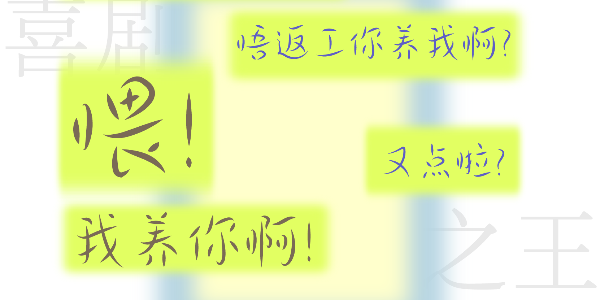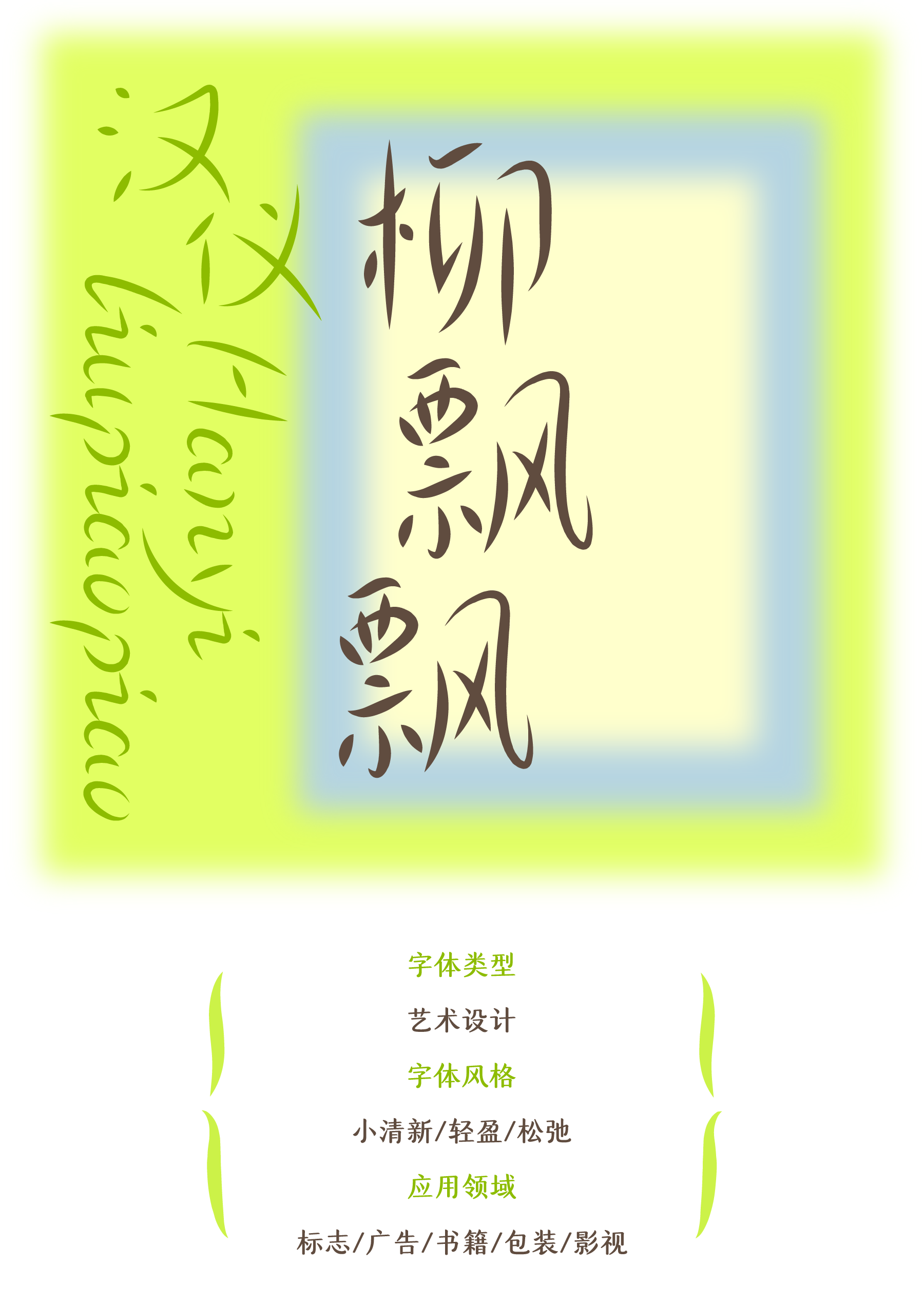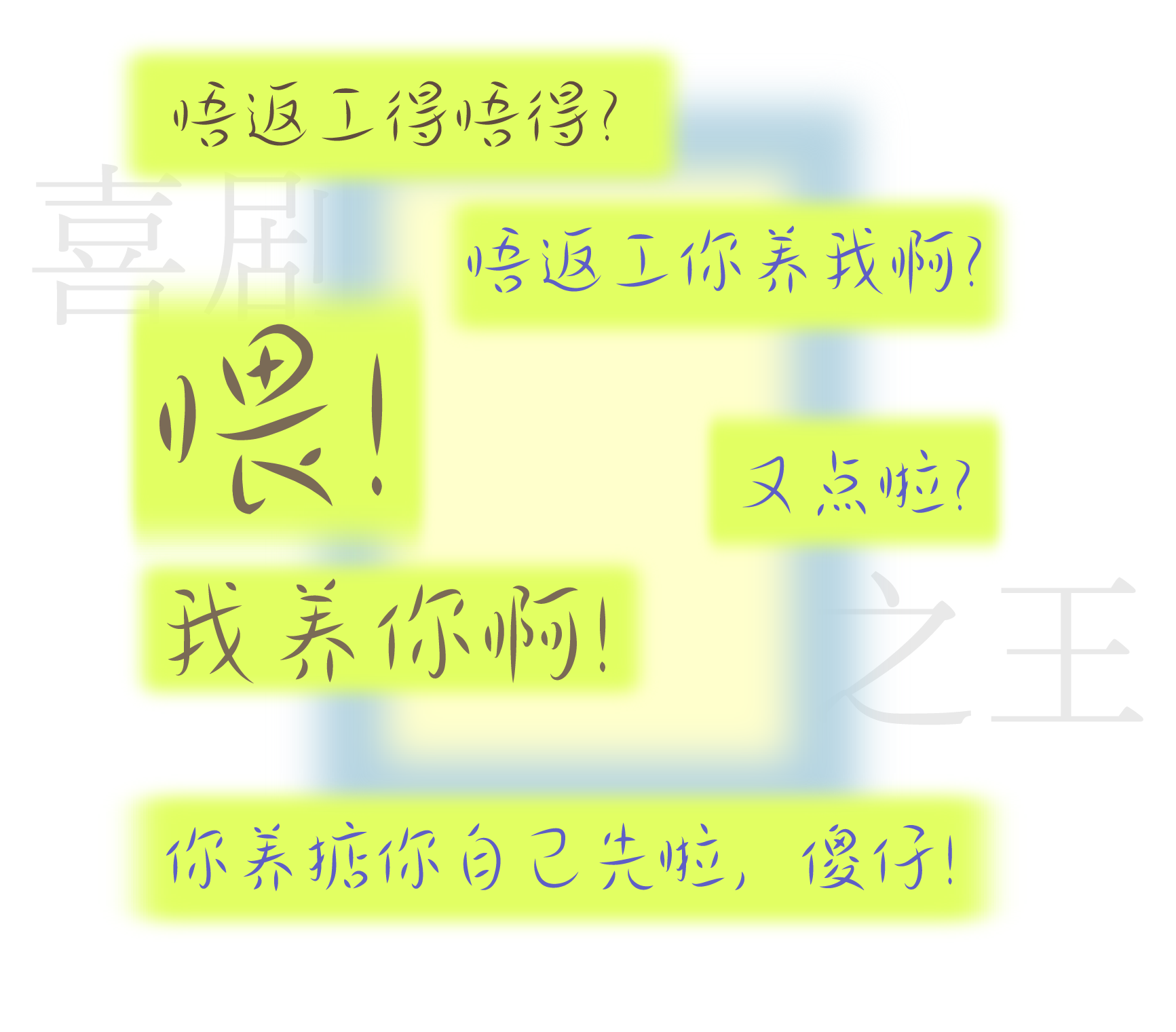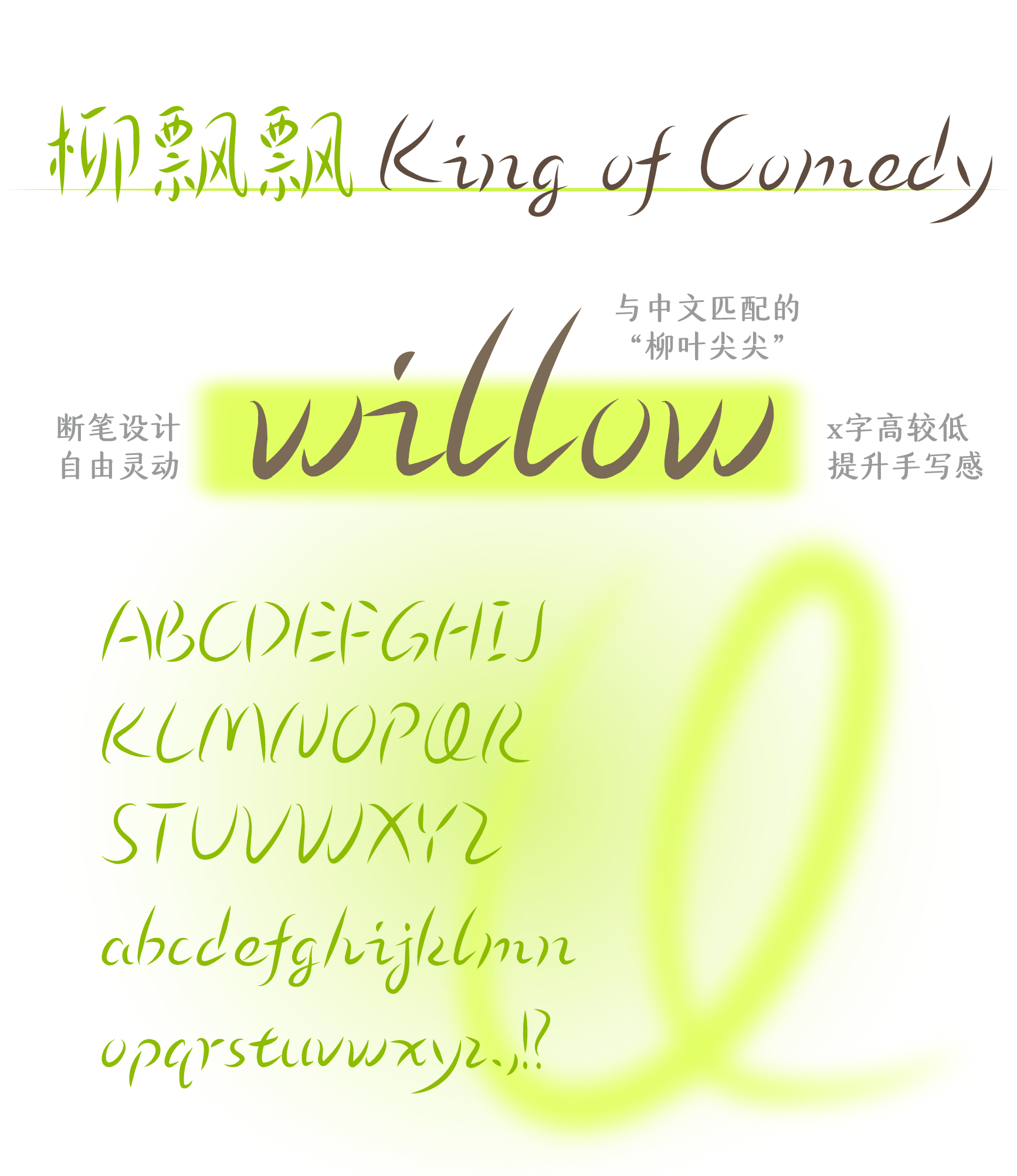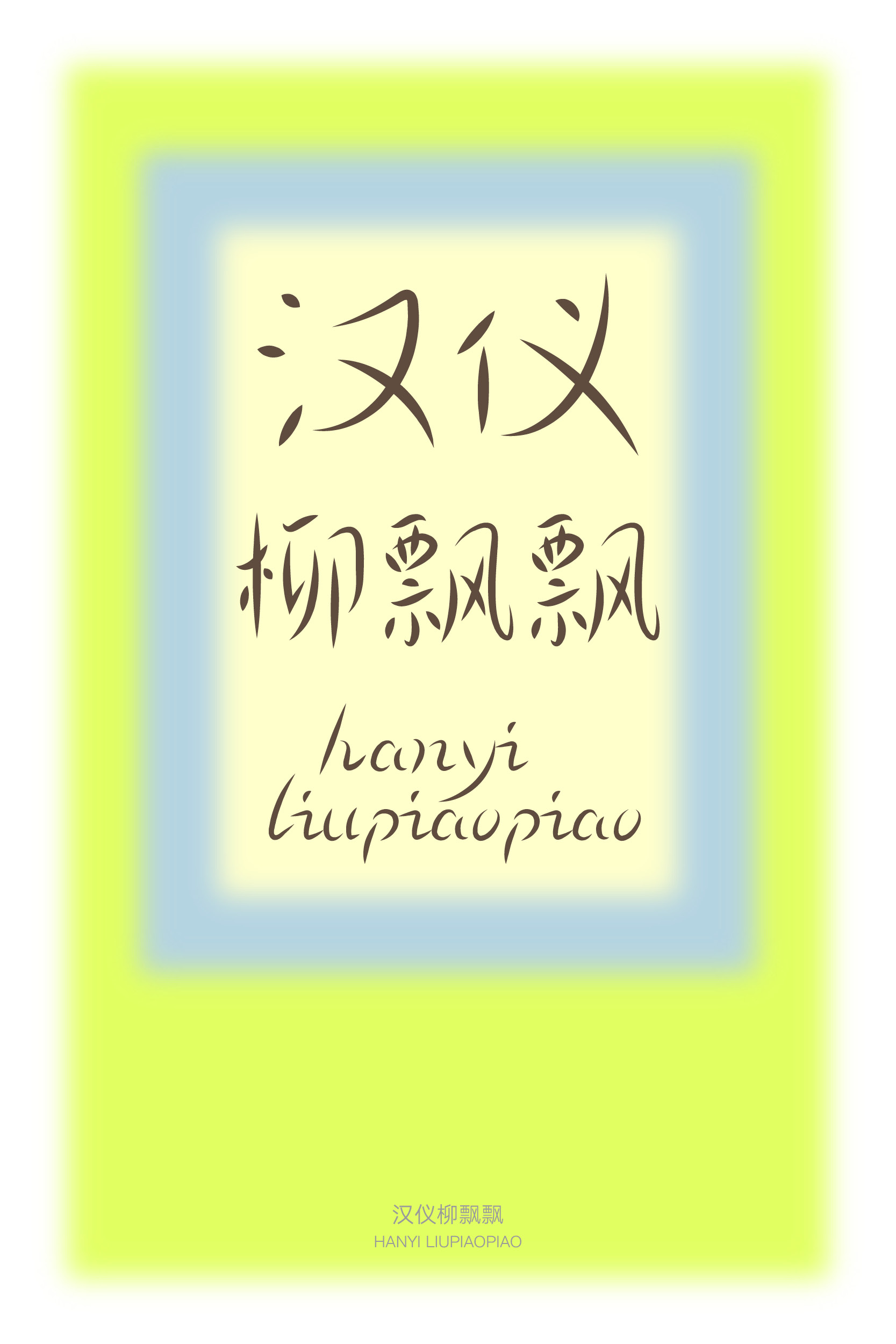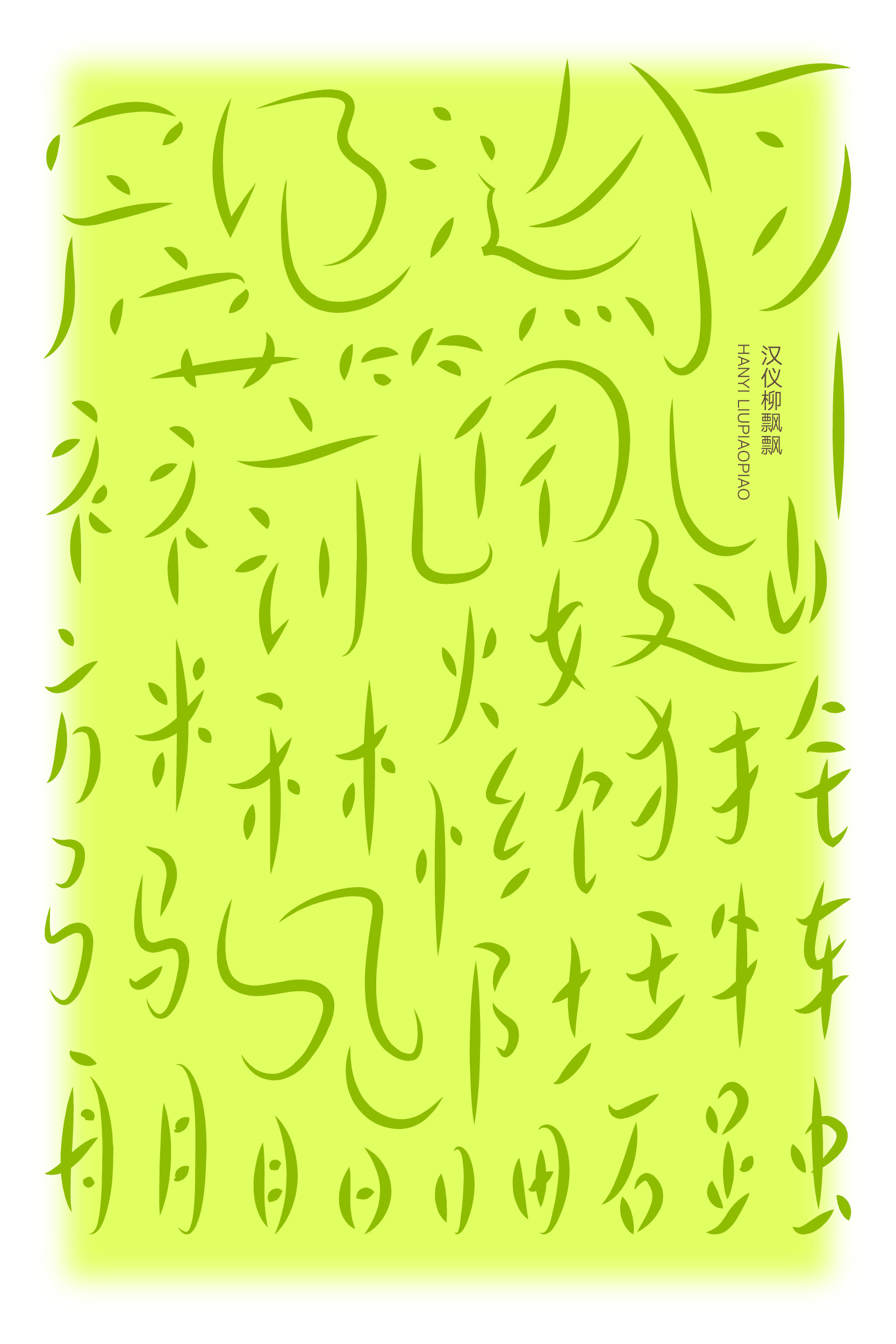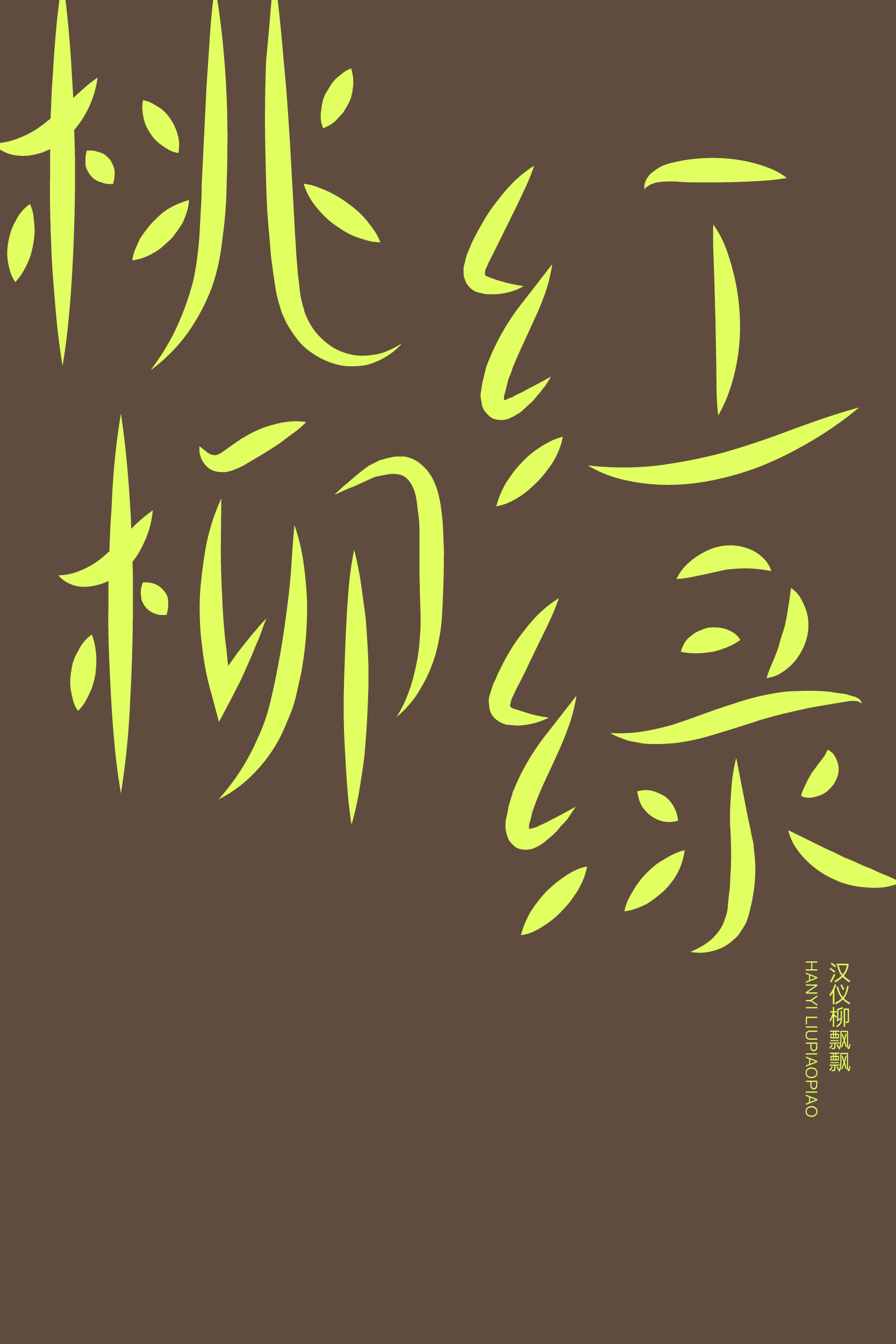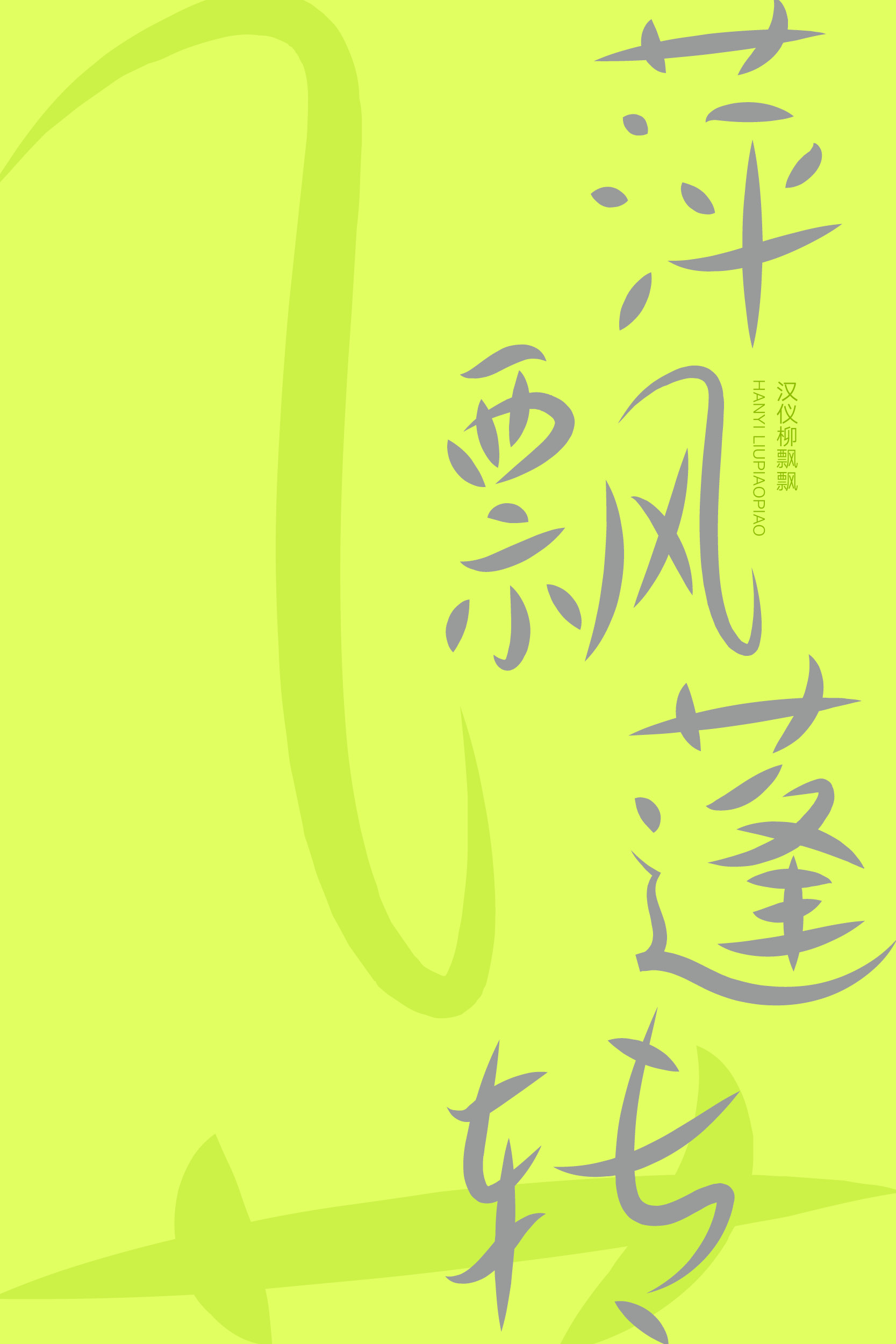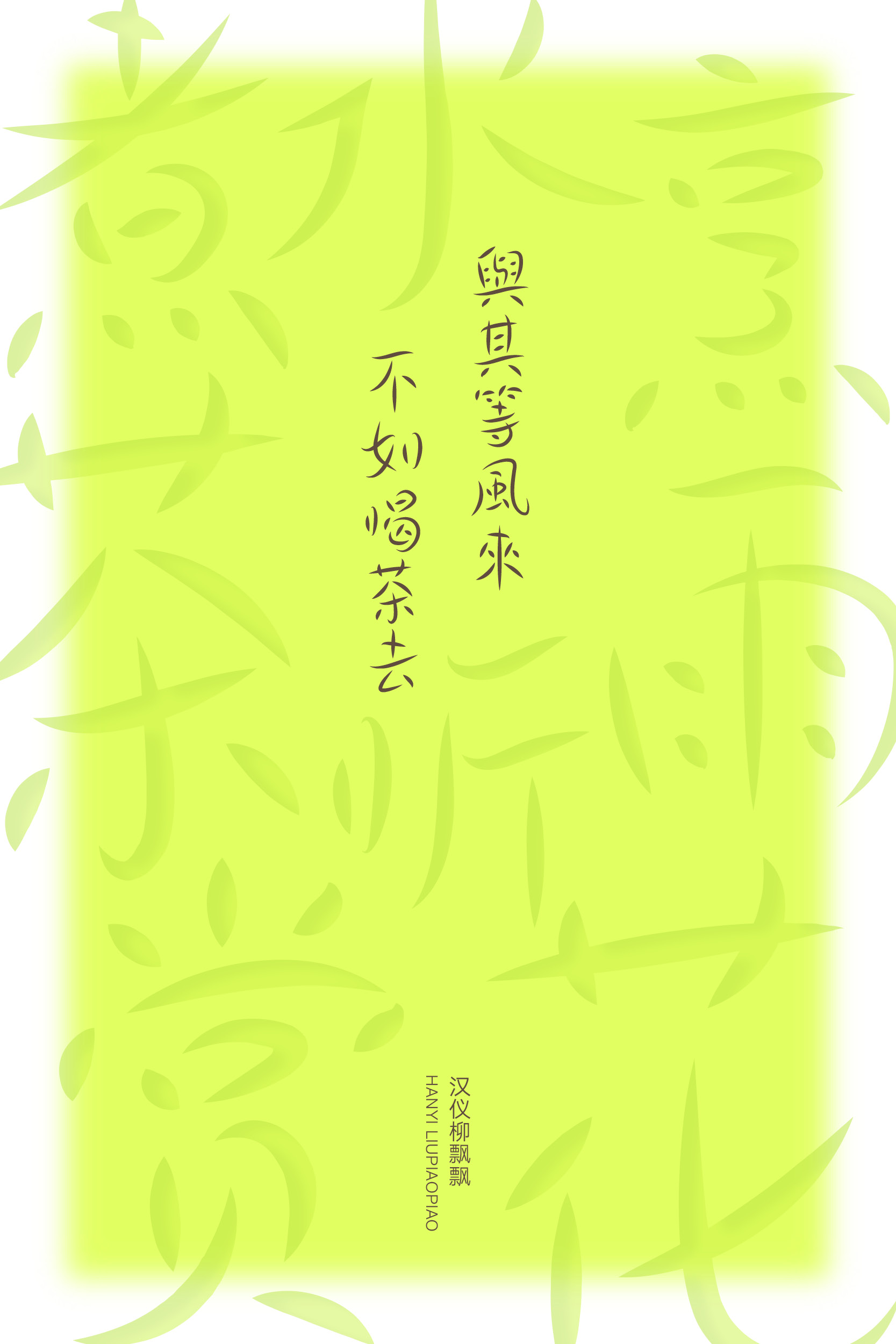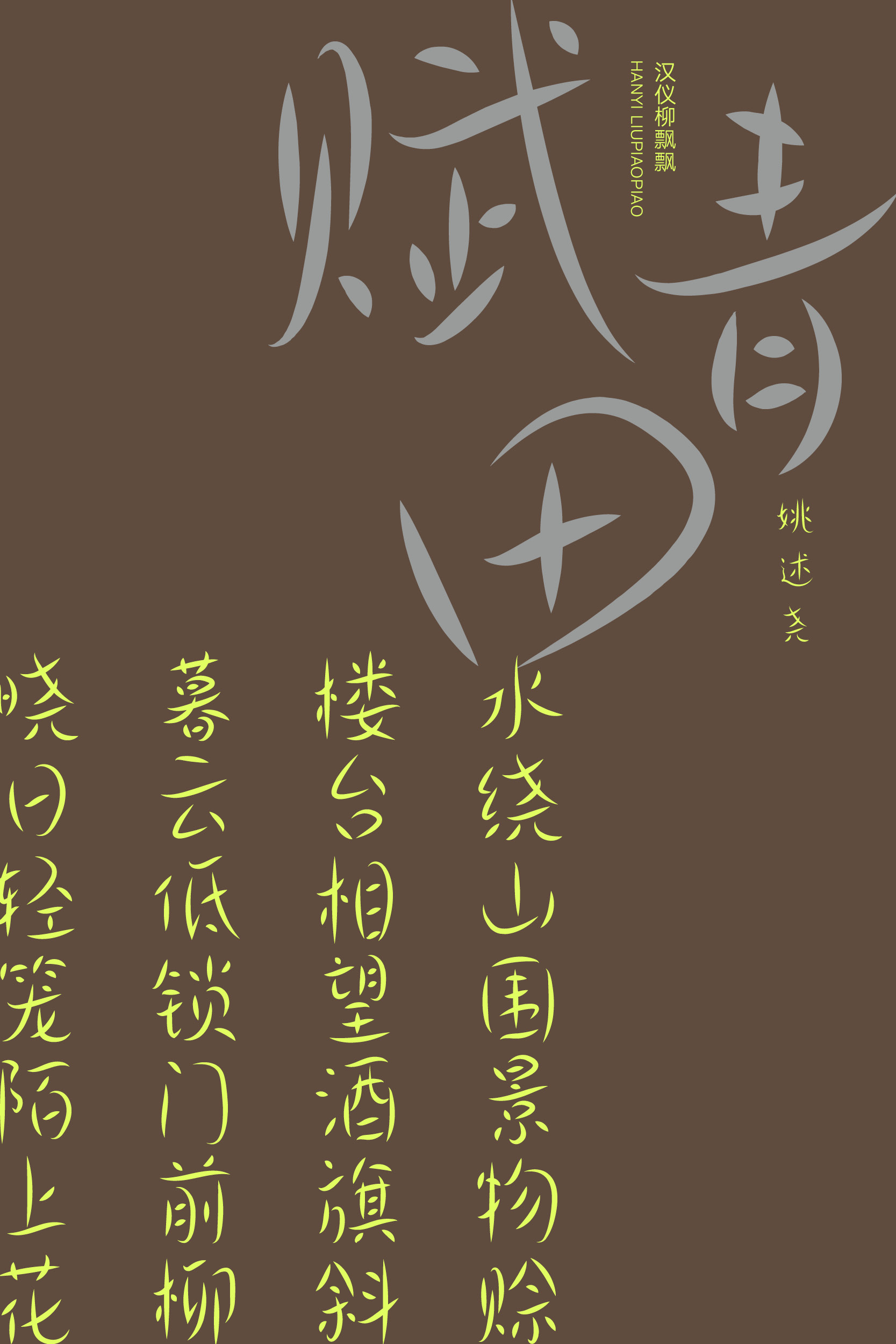
柳叶似明月,飘飘春意来~
“不知细叶谁裁出,二月春风似剪刀”,柳叶似明月,如碧眼,绕指间,柔媚而韧心。古往今来,“柳文化”以其独特意蕴在中国传统文化与现代生活中占据一席之地,人们以柳代春,以柳喻人,借柳抒情。汉仪柳飘飘以柳叶为元素,放大柳叶本身给人轻松愉悦、春意盈盈的感受,笔画上,结合柳叶“两头尖尖”、形态多变的具象特征加以设计。这款字体适合用于较短文本的排版,具有点缀装饰的功能,渲染春日清新浪漫的气息。
汉仪柳飘飘以柳叶为元素,柳丝飘拂,放大柳叶本身给人轻松愉悦、春意盈盈的感受。
字型上,追求轻盈活泼、清晰疏朗之感,如晚风吹拂,气质独特,同时兼顾了阅读舒适性。
笔画设计以柳叶为元素,轻盈而飘忽。结合柳叶两头尖尖、形态多变的具象特征,灵动自然,清新脱俗。
整体将具象元素的抽象意蕴与现代风格巧妙结合,淡雅灵动。这款字体适合用于较短文本的排版,具有点缀装饰的功能,增添画面活力,渲染春日清新浪漫的气息。
这款字体的西文部分同样以柳叶为笔画,轻盈疏朗,中西文搭配使用可以满足更广泛的应用场景,渲染春日气息。